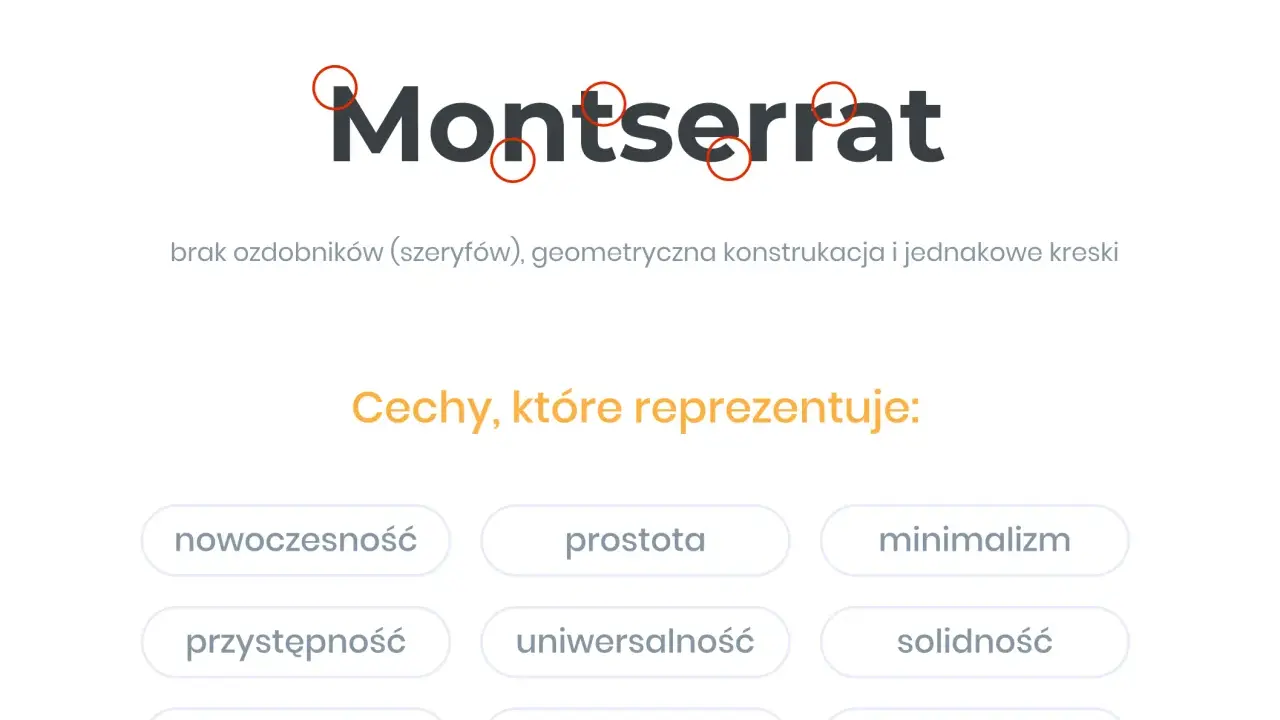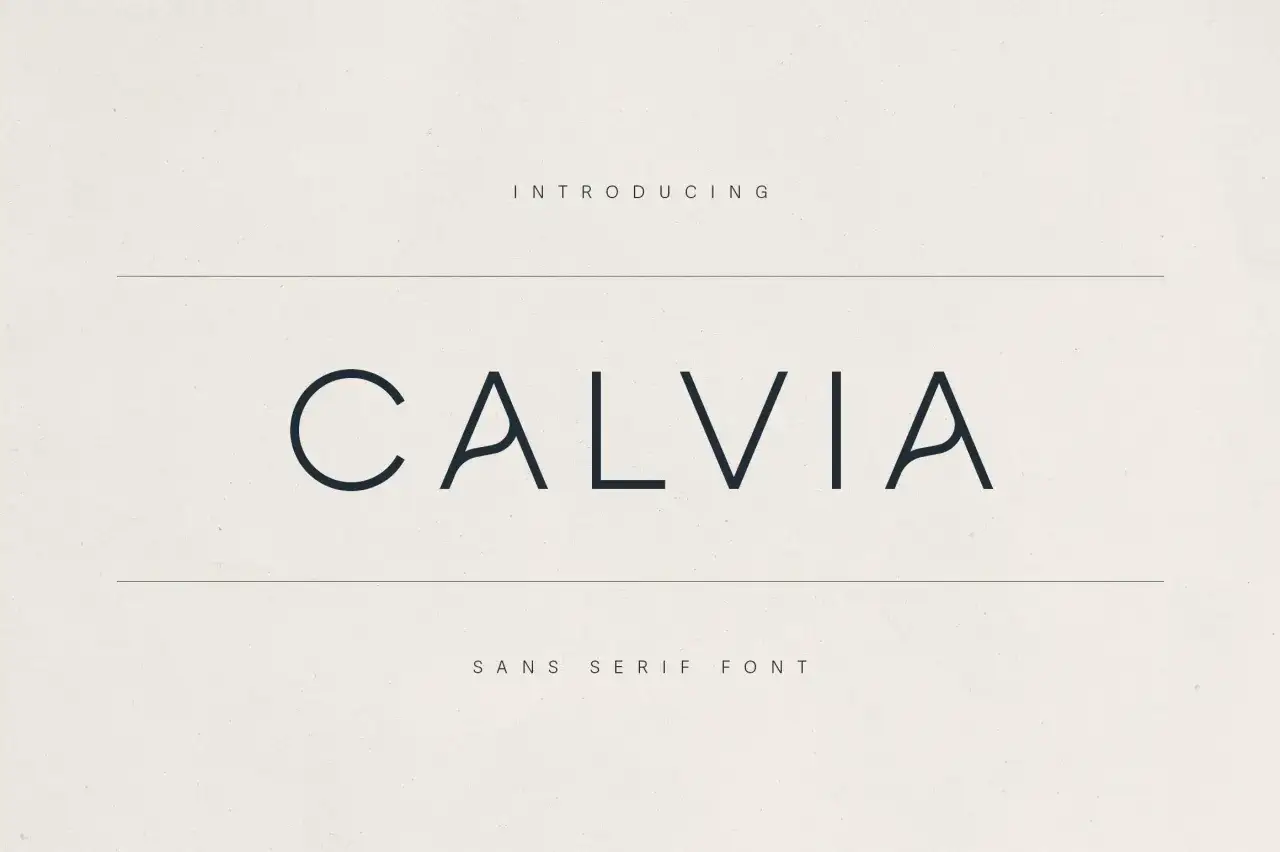
Kroje do cięcia - Jak wybrać font, który nie zepsuje projektu?
Montserrat – czcionka do wycinania, bezszeryfowa, geometryczna, prosta i czytelna.
Dobrze dobrany krój do cięcia decyduje o tym, czy napis wyjdzie czysto w folii, papierze, kartonie albo przy prostym oznaczeniu na biurku. W praktyce najwięcej problemów sprawiają nie same litery, tylko zbyt cienkie, zbyt ozdobne albo źle przygotowane do pracy w programie. Poniżej pokazuję, jak rozpoznać bezpieczny wybór, kiedy lepiej sięgnąć po stencil, a kiedy po prosty bezszeryfowy krój, oraz jak uniknąć błędów przy konwersji tekstu na krzywe.
Najkrócej: wygrywa prostota, grubość i porządek w literach
• Do wycinania najlepiej sprawdzają się kroje bezszeryfowe, gładkie i bez drobnych ozdobników.
• Fonty szeryfowe i dekoracyjne da się użyć, ale zwykle wymagają większego formatu albo korekty w programie.
• Przy pismach odręcznych trzeba połączyć litery, inaczej każda będzie cięta osobno.
• Przed cięciem warto zamienić tekst na krzywe i sprawdzić kerning, czyli odstęp między parami liter.
• Najlepszy test to mały próbny wycinek na skrawku materiału, zanim zużyjesz właściwy arkusz.
Elegancka czcionka do wycinania CALVIA, sans serif, idealna do nowoczesnych projektów graficznych.
Jak rozpoznać krój, który nie rozsypie się przy cięciu
Ja patrzę na font z bardzo prostego punktu widzenia: nie jak na dekorację na ekranie, tylko jak na zestaw kształtów, które ma przejść ostrze. Jeśli litera ma cienkie końcówki, mocny kontrast grubości albo mnóstwo drobnych ozdób, ryzyko rośnie od razu. W cięciu liczy się przede wszystkim czytelność konturu, a dopiero później charakter.
Najbardziej problematyczne są kroje, w których detal jest ważniejszy niż konstrukcja. Cienkie szeryfy, falowane zakończenia, fakturowane powierzchnie czy bardzo wąskie światła liter potrafią wyglądać świetnie w druku, ale przy nożu albo ploterze rozjeżdżają się na etapie samego cięcia. Jeśli element ma być mały, ta różnica wychodzi jeszcze wyraźniej.
Na co patrzeć w pierwszej kolejności
• Grubość kreski - im bardziej równomierna, tym bezpieczniej.
• Otwory wewnętrzne liter - zbyt małe oczka w literach takich jak a, e, o czy p są trudne do wycięcia i późniejszego oczyszczenia.
• Ilość detali - każdy ozdobnik, zakończenie i dodatkowy zawijas zwiększa ryzyko błędu.
• Kontrast - mocna różnica między grubymi a cienkimi fragmentami litery zwykle szkodzi przy cięciu.
Jeśli projekt ma być użyty jako szablon, szukałbym raczej kroju szablonowego. Gravotech zwraca uwagę, że przy szablonach warto używać krojów TTF typu stencil, bo inaczej łatwo zgubić wewnętrzne fragmenty liter takich jak e czy a. To praktyczna wskazówka, nie ozdobnik z katalogu typograficznego.
W takim podejściu najważniejsze pytanie brzmi nie „czy to wygląda elegancko”, ale „czy nożyk i materiał poradzą sobie z tym bez strat”. Od tego zależy, czy lepiej wybrać klasyczny sans, stencil, czy coś bardziej kaligraficznego.
Które style typograficzne naprawdę działają w praktyce
Jeżeli miałbym ustawić bezpieczny ranking, zacząłbym od prostych krojów bezszeryfowych, a dopiero potem przeszedłbym do bardziej charakterystycznych rozwiązań. W Cricut Design Space filtr kerned pomaga znaleźć fonty z lepszym odstępem między literami, co przy wycinaniu oszczędza sporo ręcznej poprawy. Taki filtr nie rozwiązuje wszystkiego, ale porządkuje wybór na starcie.
Styl Gdzie działa najlepiej Na co uważać Mój praktyczny komentarz
Bezszeryfowy Etykiety, tabliczki, napisy biurowe, proste oznaczenia Zbyt cienkie warianty i zbyt mały format To najbezpieczniejsza baza, gdy liczy się czytelność i szybkie cięcie.
Szeryfowy Większe napisy dekoracyjne i bardziej klasyczne kompozycje Szeryfy łatwo się urywają przy małym rozmiarze Sprawdza się, ale raczej w większej skali niż przy drobnym napisie.
Stencil Szablony, malowanie przez maskę, techniczne oznaczenia Mostki muszą być na tyle szerokie, by litera się nie rozpadła Najbardziej sensowny wybór, gdy potrzebujesz kontroli nad wnętrzem liter.
Script lub handwriting Zaproszenia, dekoracje, napisy z charakterem Konieczne łączenie liter i pilnowanie grubości połączeń Piękny efekt, ale tylko wtedy, gdy przygotujesz litery do wspólnego cięcia.
Single-line Grawer, rysowanie, niektóre maszyny CNC Nie jest to klasyczny krój do pełnego wycinania liter z folii Świetny do linii i zapisu technicznego, słabszy do wycinania zamkniętych kształtów.
W codziennej pracy najczęściej wybieram bezszeryfowy krój o równych proporcjach. Dla etykiet na segregatorach, organizerów, tabliczek na półki czy prostych oznaczeń w biurze to po prostu najrozsądniejsze rozwiązanie. Jeśli zależy ci na bardziej dekoracyjnym efekcie, dopiero potem sięgałbym po szeryfy albo delikatną kaligrafię.
Tu dobrze widać różnicę między typografią „do oglądania” a typografią „do cięcia”. Obydwie mogą być estetyczne, ale druga musi jeszcze wygrać z materiałem i narzędziem.